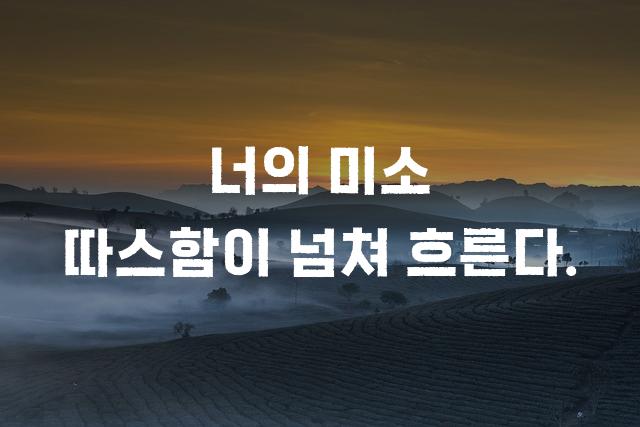
감탄로드 탄탄체는 기본적인 고딕 스타일을 갖춘 폰트로, 제목용으로 디자인되었습니다. 세련되고 명료한 라인이 특징으로, 강원특별자치도와 투게더그룹의 협력으로 탄생했습니다.
감탄로드 탄탄체은(는)
기본 고딕, 감성적인, 부드러움, 길고/크고 계열의 생김새를 가지고 있으며
포스터, 소셜 미디어 등에서 자주 활용되며, 효과적인 메시지 전달에 적합합니다.
이 폰트는 광고/마케팅, 엔터테인먼트 분야에 잘 어울리며,
친근한, 재미있는 느낌을 담고 있는 것이 특징입니다.